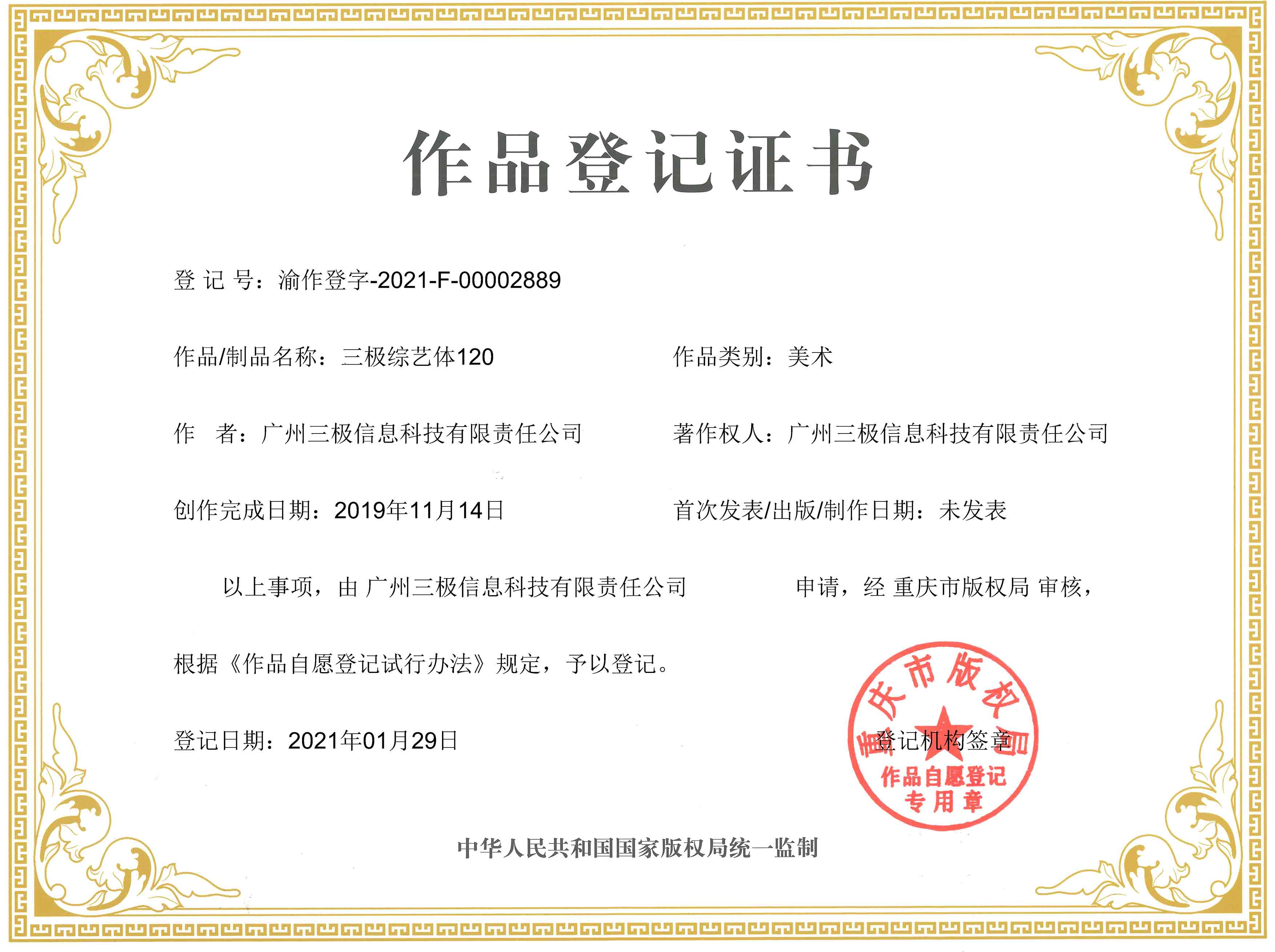
三极综艺体120
字体说明:三极综艺体120字体是一款可商用的毛笔书法,英文手写,手写体字体,该字体包含6763个中文、字母、符号和数字,具有充满力量、大气、豪放、稳重、手写风、古典 的风格,可以满足您设计上的各种需求,该字体主要用于电商、广告、视频影视、海报企宣、书籍 等场景, 您不但可以在字格网下载三极综艺体120,同时还有众多毛笔书法字体、创意字体等可供选择!